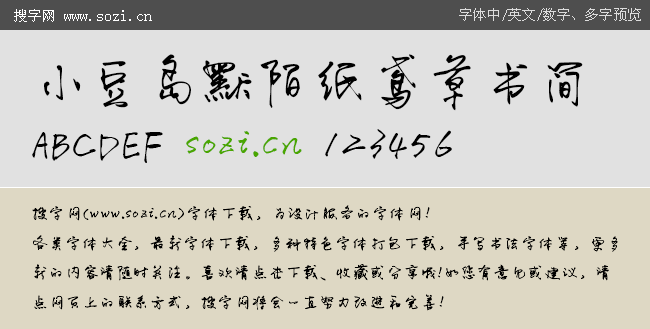
小豆島默陌紙鳶草書簡(jiǎn)
搜字網(wǎng)提供一款小豆島默陌紙鳶草書簡(jiǎn)中文字體下載,小豆島默陌紙鳶草書簡(jiǎn)是款很有個(gè)性的字體。字庫(kù)非常豐富,而且字體特效非?犰,以草書為基礎(chǔ),形體狂放、大氣,適合應(yīng)用于海報(bào)設(shè)計(jì)、書籍裝幀、畫冊(cè)封面、產(chǎn)品包裝設(shè)計(jì)等應(yīng)用。